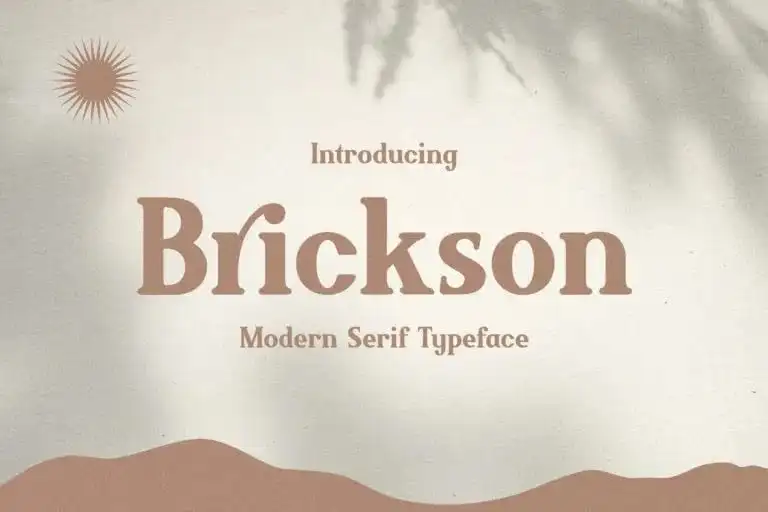
A Brickson Serif Font é uma escolha perfeita para quem busca uma tipografia serifada sofisticada e elegante. Oferecida pela TypeFactory através do 99designs, esta fonte carrega um estilo bold que se sobrepõe a formas redondas, garantindo uma leitura fluente e um excelente equilíbrio entre os elementos visuais de headlines e textos. Ela é ideal para projetos variados, desde anúncios atrativos até design editorial delicado. A Brickson não apenas oferece o conforto e elegância que você espera em uma tipografia serifada, mas também permite um máximo de versatilidade ao usar-a em uma ampla gama de trabalhos gráficos. Com sua elegância cuidadosamente elaborada, a fonte é fácil de combinar com projetos de todos os tipos, transformando qualquer design em algo refinado e único.